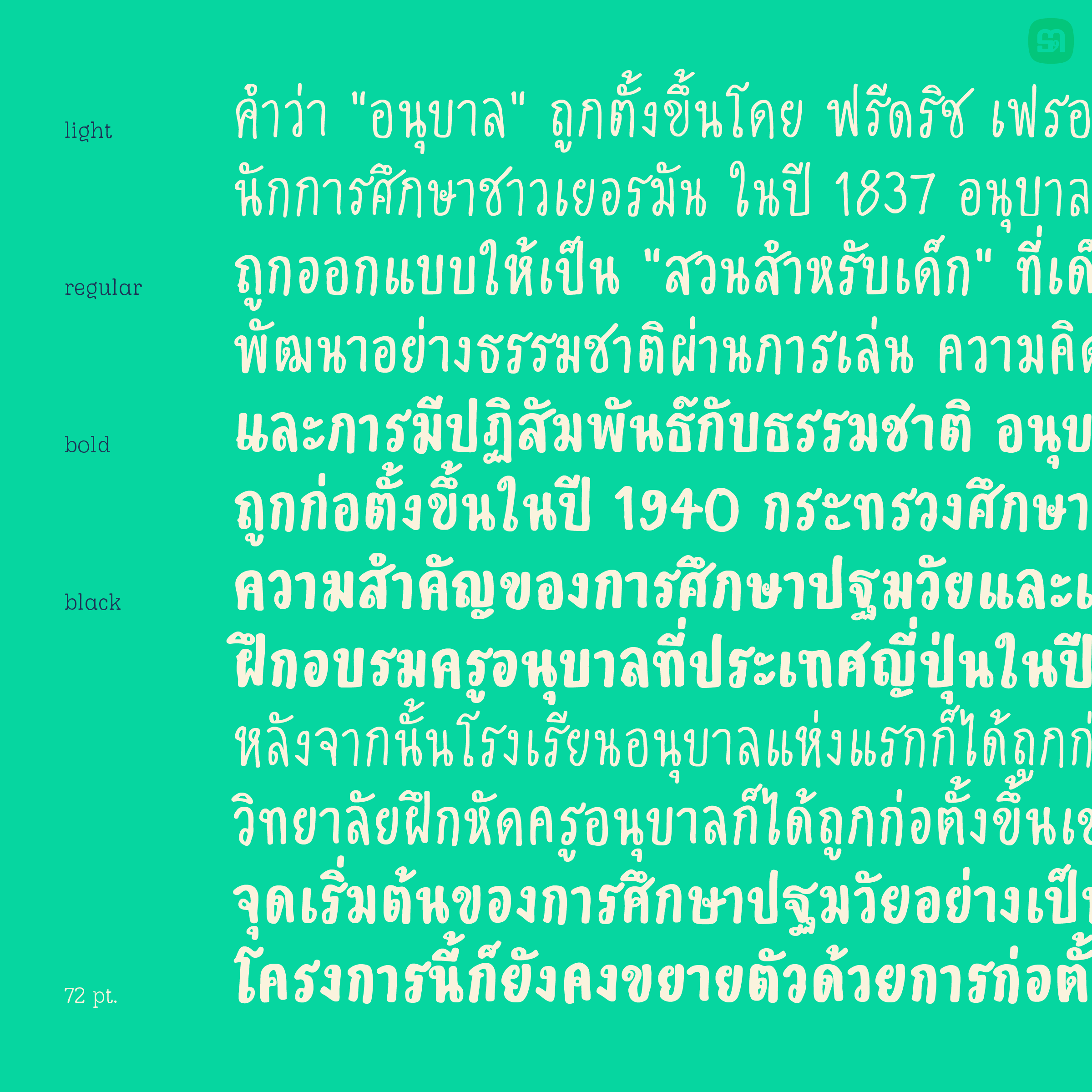
เด็กชายโปเต้ | KIDDO POTAE
ว่าที่ฟอนต์ลายมือเด็กที่แจ่มว้าวที่สุดในสยามประเทศ
ชื่อฟอนต์ : เด็กชายโปเต้ | KIDDO POTAE
เด็กชายโปเต้ | KIDDO POTAE
ฟอนต์ลายมือเด็กที่ครบถ้วน สมบูรณ์
และแจ่มว้าวที่สุดในสยามประเทศ
เพิ่มเติมด้วยการขยายขอบเขตการใช้งานออกไป
ด้วยชุดอักษรถึง 3 แบบ ไม่ซ้ำ แม้จะพิมพ์ด้วยข้อความเดิม
รองรับการใช้งานได้หลากหลายภาษา
ไม่ว่าจะเป็นภาษาไทย ภาษาอังกฤษ รวมทั้งภาษาภาคพื้นยุโรปอีกมากมาย
เพิ่มความพิเศษด้วย OpenType Features ต่าง ๆ
ไม่ว่าจะเป็นการจัดการสระ / วรรณยุกต์ไทย ด้วย Anchor Marking, Ligatures, การทำ Kerning เพื่อความสวยงาม
ชุดฟอนต์ "เด็กชายโปเต้"
ประกอบด้วยฟอนต์ 4 น้ำหนัก 4 ฟอนต์
• KIDDO POTAE LIGHT / REGULAR / BOLD / BLACK
ออกแบบโดย : Montonn Thanaroj
ฟอนต์ 4 น้ำหนัก
ในแต่ละน้ำหนัก มี 3 ชุดตัวอักษร
สลับหมุนเวียนด้วย contextual alternates (calt)
ฟอนต์ลายมือเด็กผู้ชายที่ดีที่สุดในสยามประเทศ